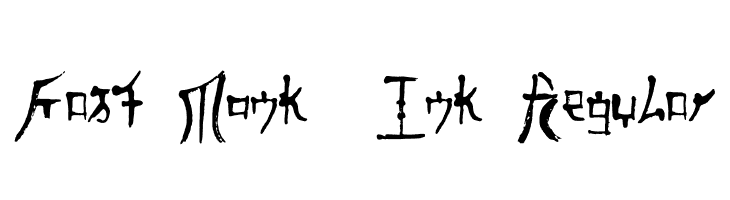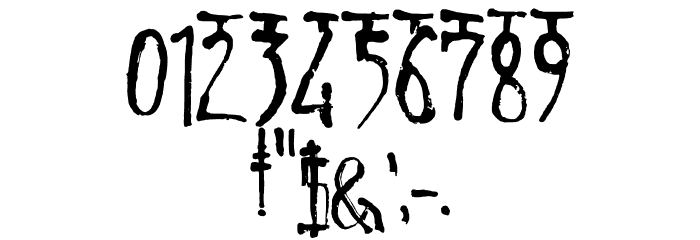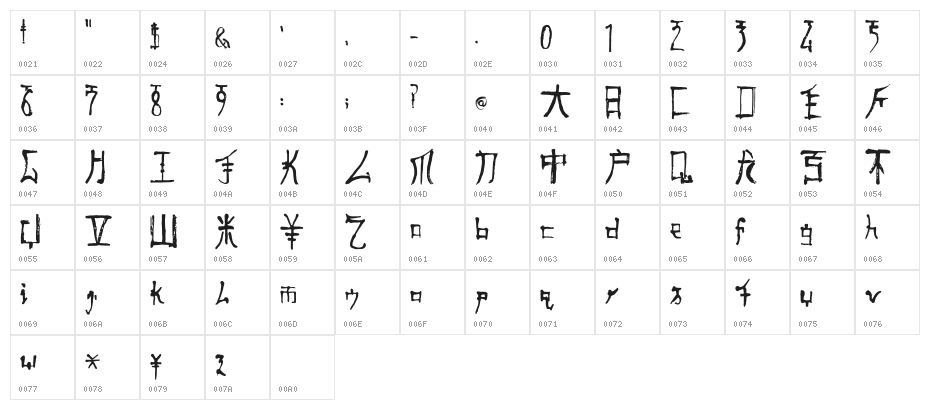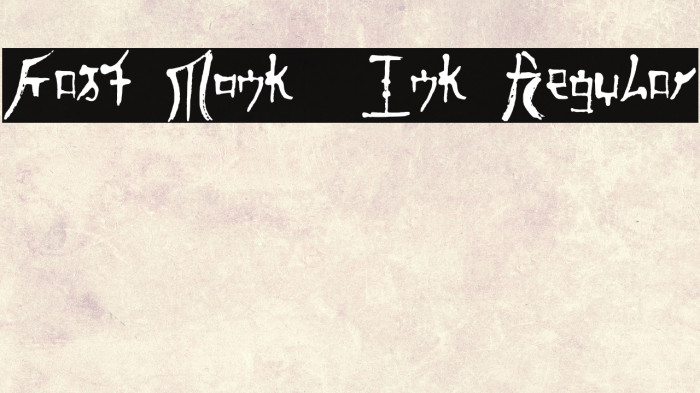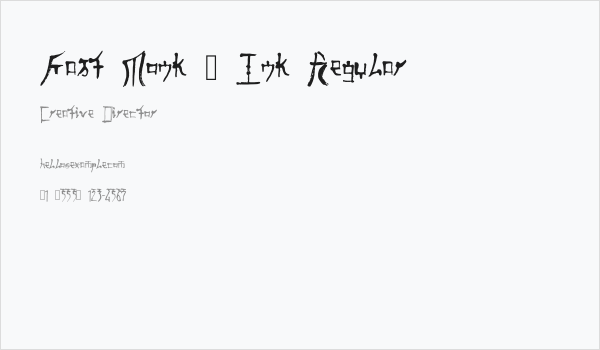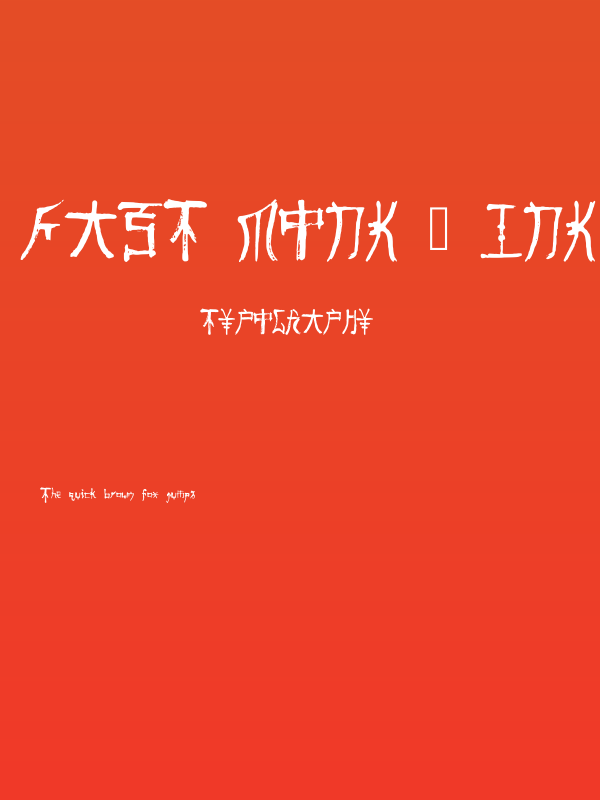
Fast Monk _ Ink Regular Font
✎ Thick
| Название | Fast Monk _ Ink Regular |
| Семейство шрифтов | Fast Monk _ Ink |
| Категория | Thick |
| Общий стиль | Modern, Artistic |
| Рекомендуемые проекты | Ideal for creative projects such as posters, album covers, and branding that require a distinctive and artistic touch. |